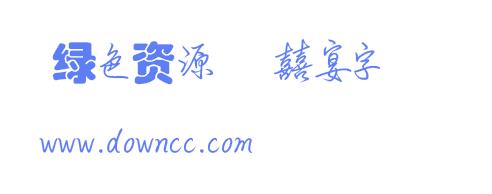
oppo簡(jiǎn)囍宴體是一款十分好看的字體,同時(shí)也支持在華為手機(jī)上使用在電腦上使用,讓你能夠獲得最精美的字體視覺效果,更有很不錯(cuò)的視覺風(fēng)格,讓你在欣賞這款字體的同時(shí)獲得不錯(cuò)體驗(yàn)!
這款字體確實(shí)擁有十分精美的行文結(jié)構(gòu),在喜宴上使用將會(huì)獲得不粗的效果,如可以運(yùn)用到喜帖上,十分不錯(cuò)。